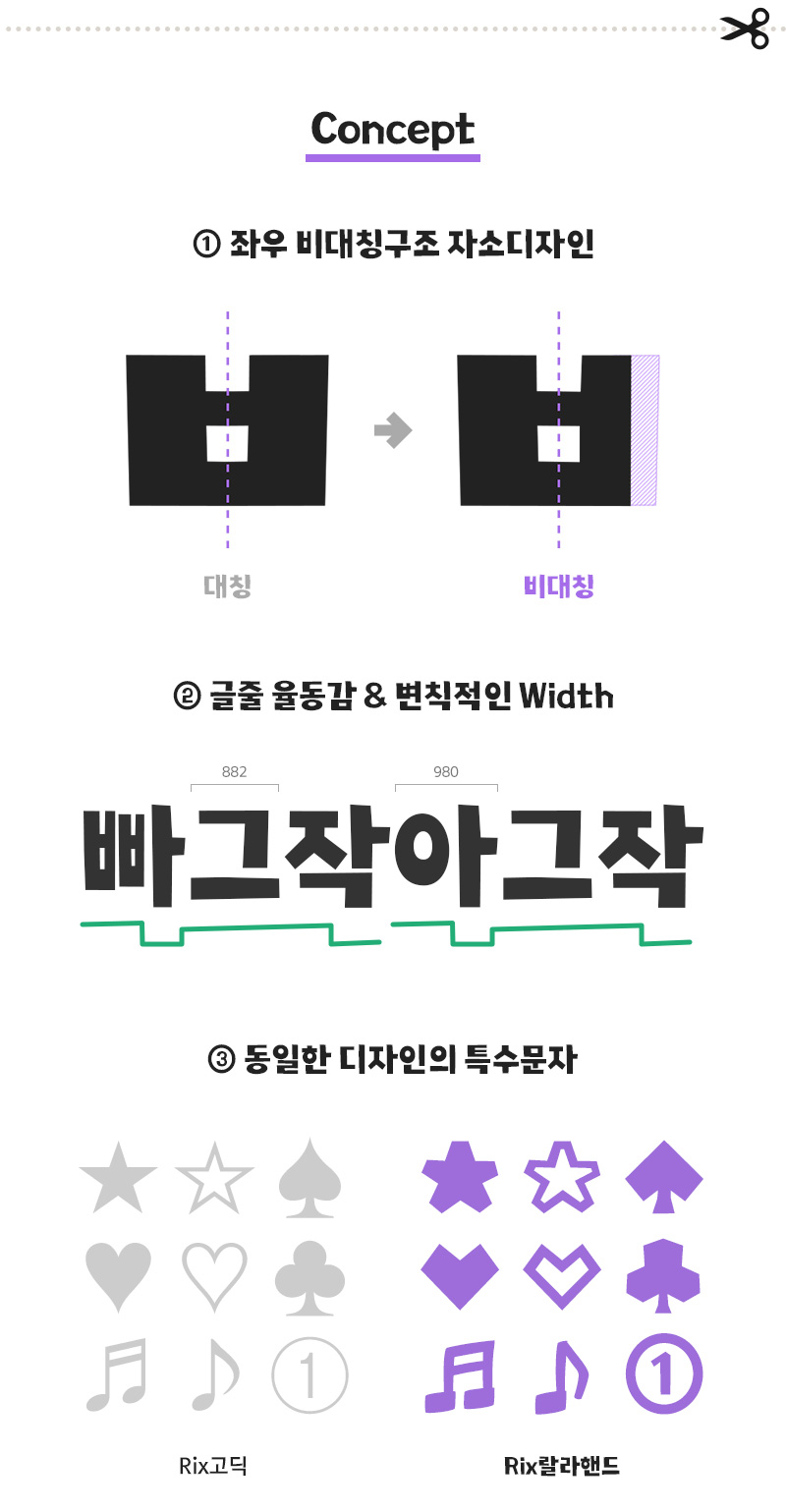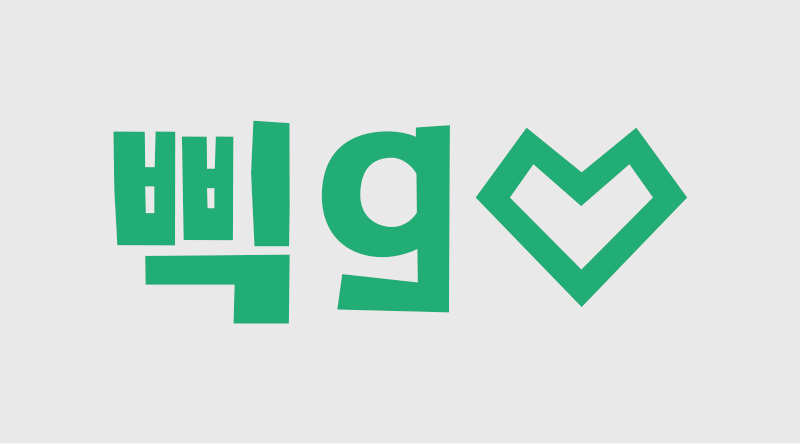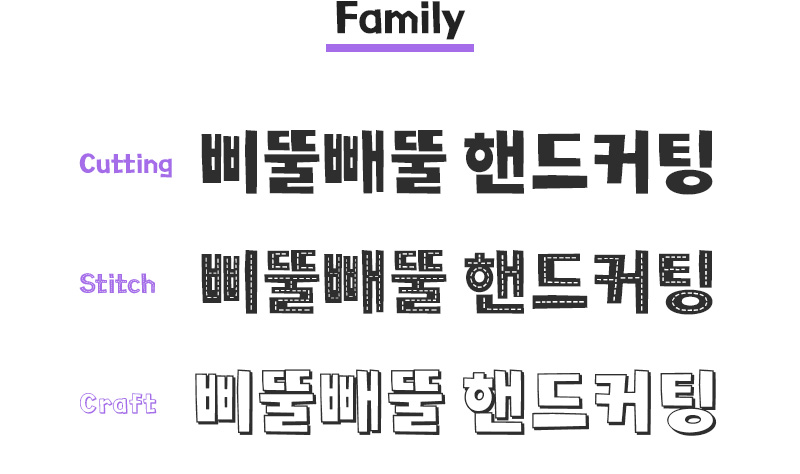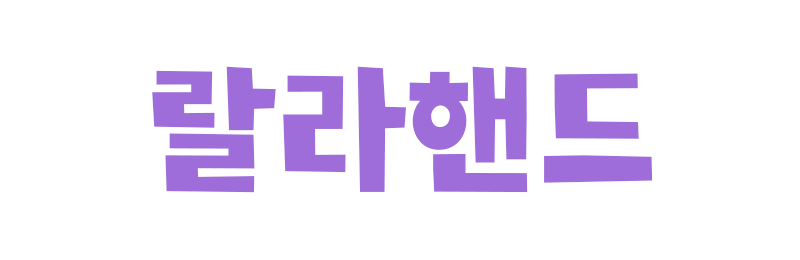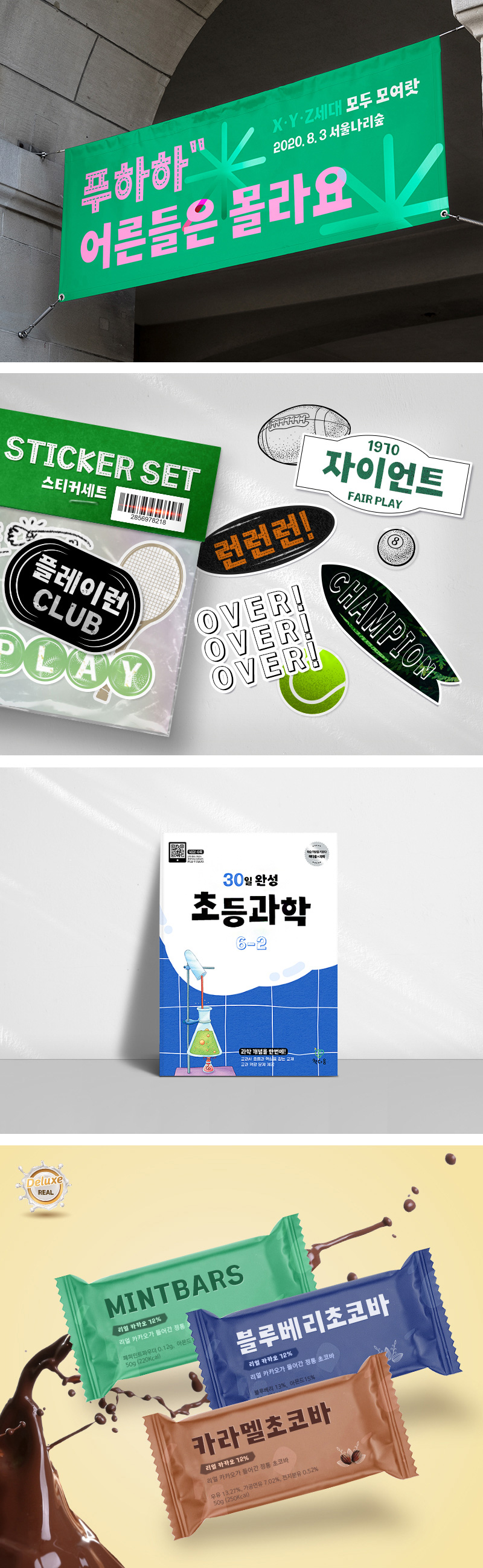
RixLalaHand
3 Style - Cutting, Stitch, Craft가위나 칼로 종이를 잘라서 만든 글자입니다. 어린시절 미술시간에 싹뚝싹둑 잘라 만들기하던 즐거운 기억을 담아 제작하였습니다.
가로세로 자유로운 획대비와 비대칭한 자소, 삐뚤빼뚤 사선의 획 마무리가 특징입니다.
| FontFamily | Rix랄라핸드 / RixLalaHand |
|---|---|